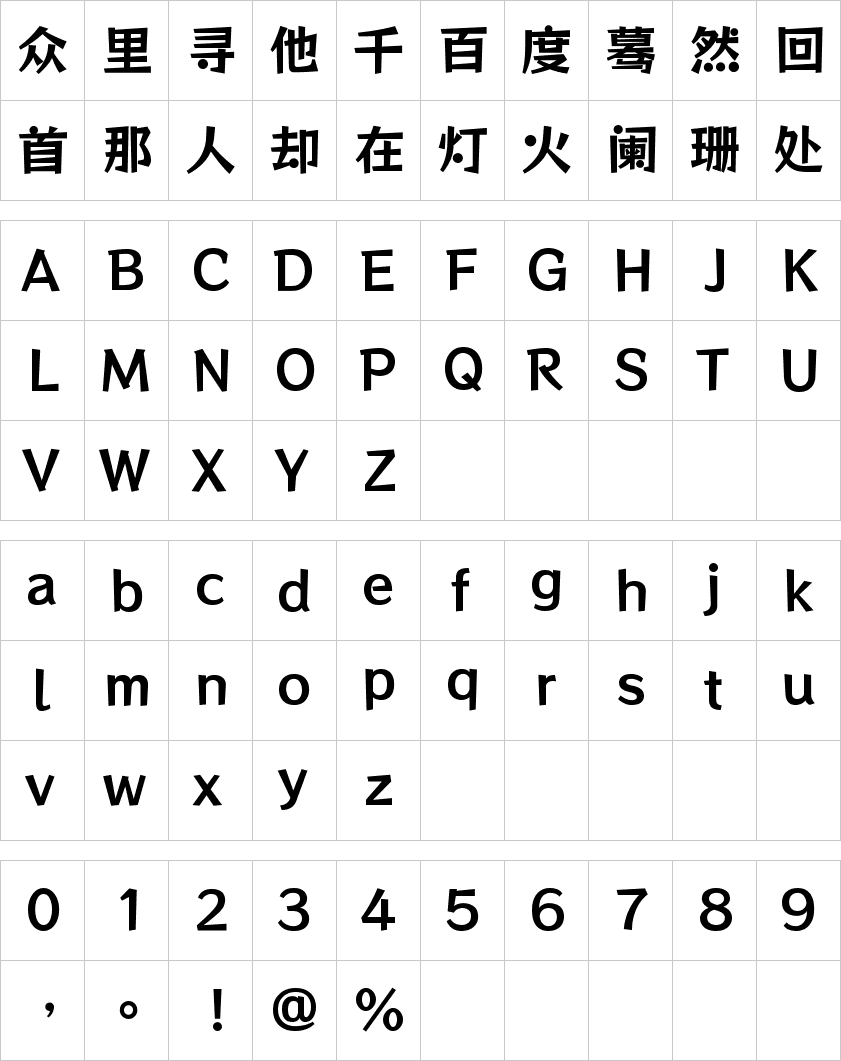
标小智龙珠体
2022年我们发布的首款免费商用字体标小智无界黑,受到了很多朋友的喜爱推荐。在2023年再次打造了一款卡通字体“标小智龙珠体”,允许任何个人和企业免费使用,包括商用用途,字体风格动感活泼俏皮可爱,非常适合用在卡通类logo设计中,来一起看看吧。
标小智龙珠体是基于日本著名字体设计公司Fontworks免费开源的摇滚乐 One(日文名:ロックンロール)字体进行简体字补充的一款字体。
标小智龙珠体采用了原始的流行风格字体,力度不同的笔触增加了动量,龙珠体整体上比较硬朗,字体笔画粗细变化制作动感,而这款字体最大的特点就是这圆点(龙珠)点缀了,用龙珠代替部分笔画,让字体变得更加生动活泼,气质也更加鲜明有记忆点,用来制作设计儿童卡通logo、标题文字、海报字效、横幅标语等等,整体效果非常赞。